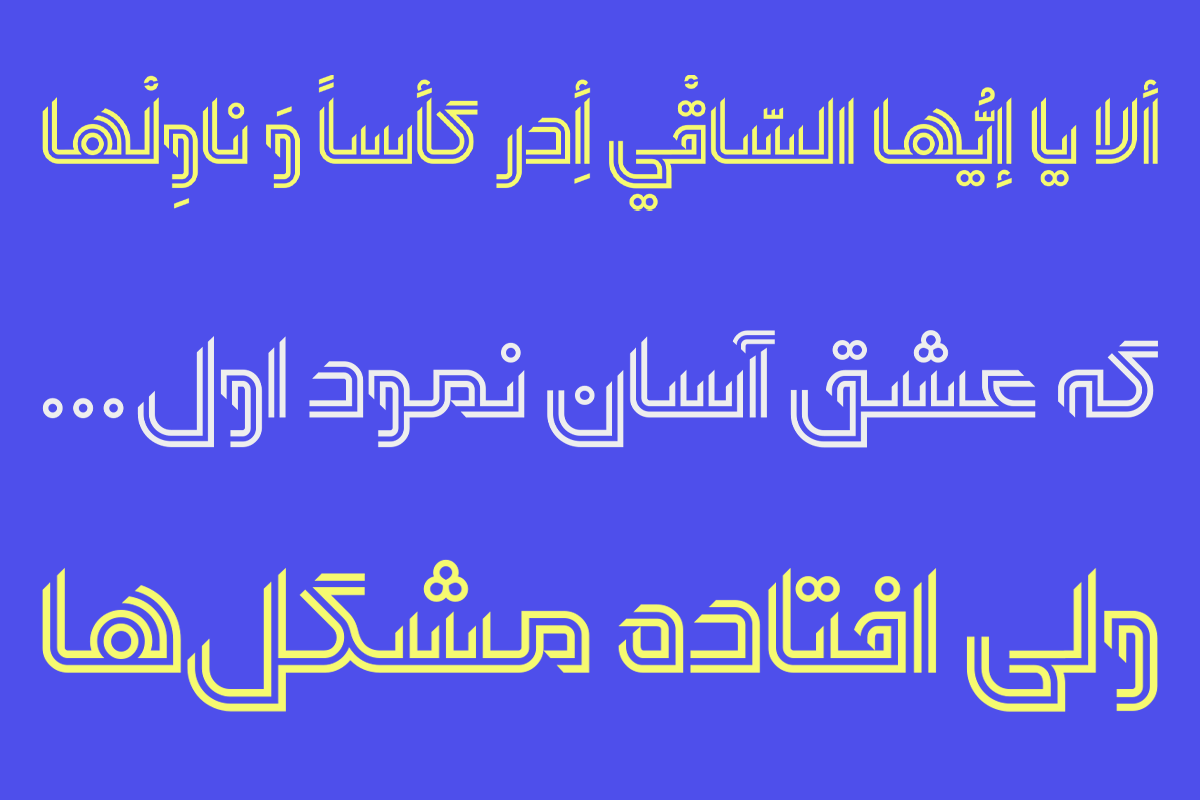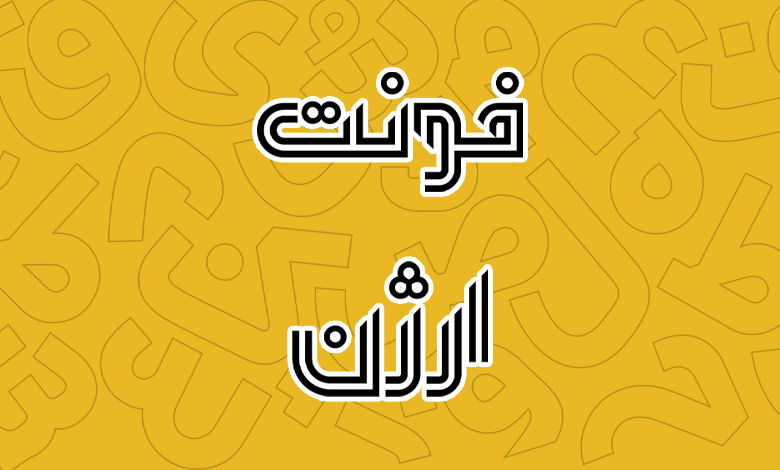
فونت ارژن (Arzhan)
فونت ارژن (به انگلیسی: Arzhan) یک فونت با ساختار هندسی و طراحی شده به صورت اینلاین (خطی) است که مناسب عناوین بوده یا اینکه میتوانید از این قلم برای کارهای گرافیکی یا تبلیغاتی استفاده کنید. در این قلم زوایای قائم در برخی حروف فاقد منحنی بوده و در مقابل برخی حروف دیگر دارای انحنای دو برابری هستند.
این فونت توسط مصطفی اوجی در سبک اینلاین درون خطی طراحی شده است که برای عنوانهای تبلیغاتی متوسط تا بزرگ، نتیجه مناسبی را در خروجی کار به شما خواهد داد. درون مایه قلم برگرفته از خط کوفی معقلی با هویت ایرانی است. امین عابدی نیز توسعه این قلم را در قالب نرمافزاری فراهم نموده است.
در ادامه این نوشته از سایت فونتچی به نقد و بررسی کامل قلم ارژن خواهیم پرداخت؛ قلمی که میتوانید از آن برای انواع محتواهایی که جنیه تزئینی داشته یا نیاز به فونتی با ساختار درون خطی دارید استفاده کنید.
سبک طراحی و وزن فونت ارژن
فونت ارژن در ساختار خطی خود دارای ظاهری نسبتا فشرده است. برخی حروف همچون «ـع، ـغ» در انتهای کلمات ارتفاع فشردهای در مقایسه با سایر حروف دارند و در مثابل برخی حروف دیگر مانند «ن، ـی» در مقایسه با آنها فشردگی کمتری را دارند.
در برخی خطوط برای حروف قائم شاهد یک برش مورب هستیم در حالی که برخی حروف دیگر برش با خط افقی کاملا را دارند. برای نمونه حرف «ن» در این قلم در بخش انتهایی دارای برش مورب بوده و نسبت به خط کرسی در ارتفاع بالاتری قرار دارد. در حالی که انتهای این حرف که قلم به پایان حرف میرسد، هم ارتفاع کمتر شده و هم اینکه برش اینلاین کاملا افقی و مستقیم است.
پشتیبانی از زبان فارسی و عربی
فونت ارژن صرفا از دو زبان فارسی و عربی پشتیبانی میکند و خبری از پشتیبانی این قلم برای زبانهای لاتین و انگلیسی وجود ندارد. اما به این معنی نیست که قلم ساختار حروف و اعداد انگلیسی را نداشته باشد. بلکه برای این زبان از فونت معمولی بهره میبرد که صد البته طراحی اینلاین ندارد.
رسم خط هر دو زبان پشتیبانی شده یکسان بوده و همین مسئله کار را سادهتر کرده است تا پشتیبانی از تمامی حروف بر اساس معیار و استاندارد همان زبان باشد. به عنوان مثال در زبان عربی که حروف «ک، ی، ه، ؤ، ئ» متفاوت از نظر حروف فارسی هستند، در این قلم به شکلهای مختلف این زبان قابل استفاده است.
کلیه اعراب برای هر دو زبان نیز علاوه بر اینکه دارای ساختار خطی اینلاین هستند، اعرابی همچون «همزه، سکون و ضمه» چون دارای شکل گرد هستند، به منظور هماهنگی با سایر حروف یک برش خطی اینلاین نیز به خود گرفتهاند. اما در مقابل برای نقاط چنین ساختاری در نظر گرفته نشده و صرفا نقاط به صورت تو خالی طراحی شدهاند.
پشتیبانی از اعداد نیز مشابه حروف استاندارد است. در زبان عربی که اعداد «۴۵۶» در مقایسه با اعداد «۴۵۶» ظاهری متفاوت دارند مانند نمونه تصویر زیر رعایت شده است که برای اعداد «۱ تا ۴» که دارای خط قائم هستند، به منظور زیبا سازی، یک زاویه جزئی در کرسی بالایی شروع نوشتن قلم درنظر گرفته شده است.
به طور کلی وقتی صفحه کلید شما روی زبان عربی یا فارسی قرار داشته باشد، این قلم بر اساس استاندارد همان زبان حروف را تایپ خواهد نمود و اختلالی از این جهت بین دو زبان با رسم خط یکسان وجود ندارد.
مناسب تبلیغات و کارهای گرافیکی تزئینی
در اینجا دو نمونه از کاربردهای این قلم را مشاهده میکنید که میتوان در هر حوزهای برای معرفی یک واحد تجاری، تبلیغات یا حتی طراحی بنرها و پوسترهایی که جدای از ساختار تبلیغاتی، جنبه تزئینی یا فرهنگی و هنری داشته باشند استفاده کرد.
همچنین در این فونت به کمک تنظیمات Open Type یا تایپ خطی که امکان کشیدهتر کردن کلمات را با تایپ کاراکترهای خاص خواهد داد، میتوانید این ساختار خطی را بدون اینکه از بین برود در ساسر حروف داشته باشید. مثلا در تصویر بالا، کلماتی مثل «گلعذاری، گلستان و جهان» به ترتیب در حروف «ـعـ، سـ و ـهـ» دارای این ویژگی هستند.